Typographies à la main – utilisations et inspiration
Les typographies dessinées à la main font un retour en temps que tendance de l’heure dans le monde du design graphique et du design web.
L’avancement technologique est probablement une des raisons pour laquelle cette tendance refait surface. De nos jours, presque n’importe qui utilise son ordinateur afin d’imprimer du texte. Résultat, on voit de moins en moins d’affiches ou d’annonces écrites à la main. Certains designers utilisent de plus en plus différentes typographies dessinées à la main afin de se détacher de la norme.
Vous retrouverez dans cet article une compilation de différentes utilisations de typographies dessinées à la main que l’on retrouve dans différents types de média.
Logos, images de marque (branding), et emballage
Dans plusieurs cas, les graphistes utilisent des images en « branding » afin de personnaliser et de donner un côté plus humain à un produit ou à une compagnie. Quoi de mieux que d’utiliser une typographie de style manuscrite afin de développer cet aspect?
Imprimerie : affiches et campagnes publicitaires
Voici deux affiches créées par l’artiste Tad Carpenter. Celui-ci utilise et intègre à la perfection ses typographies dessinées à l’intérieur de ses illustrations.
Personnellement, je trouve que les typographies dessinées apportent énormément de caractère et de personnalité aux sites web tout comme les illustrations peuvent si bien le faire. Vous trouverez ci-bas une liste de superbes sites Internet utilisant les typographies dessinées.
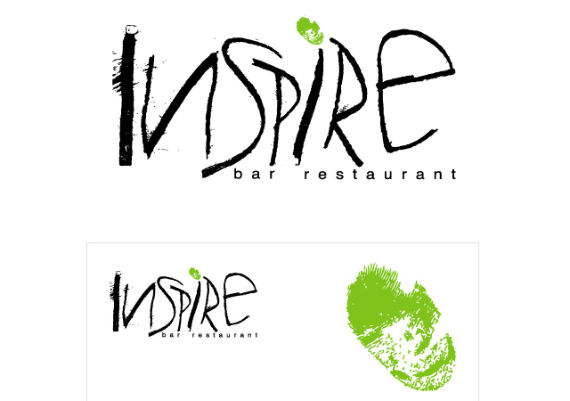
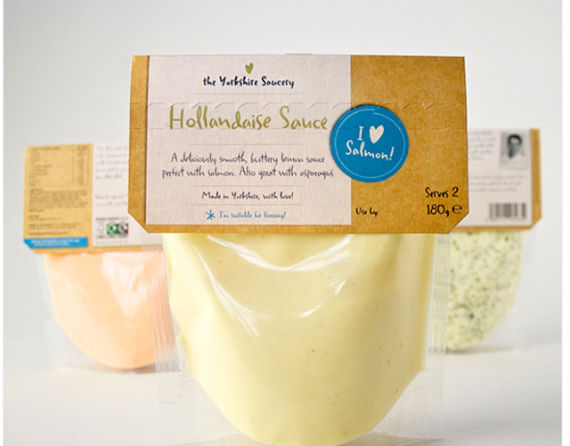
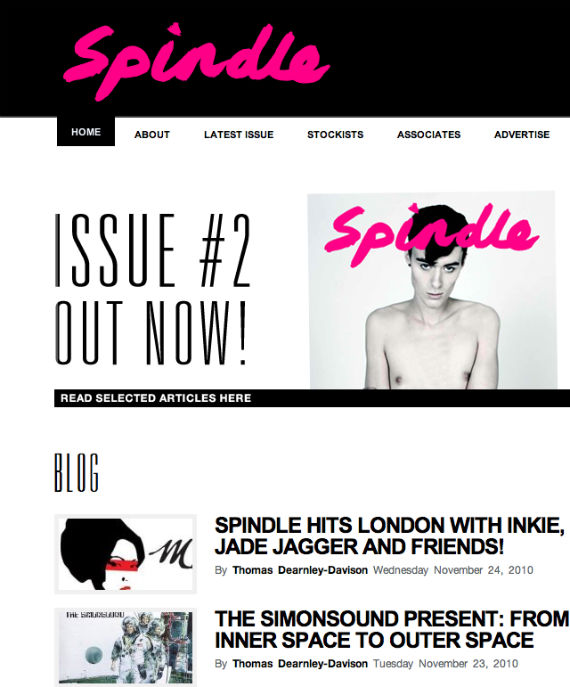
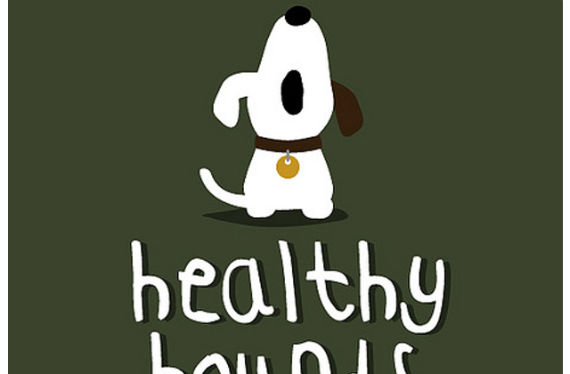
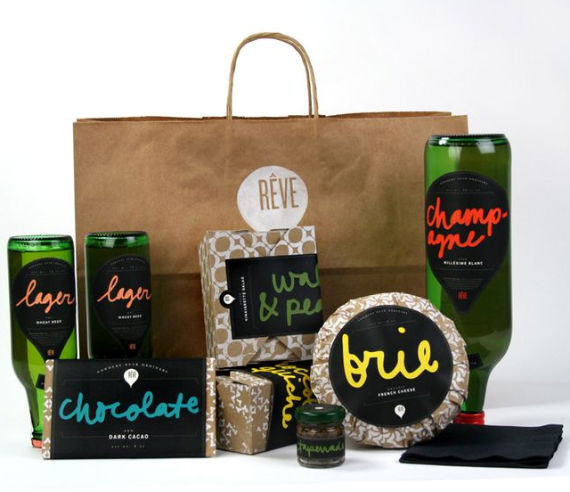
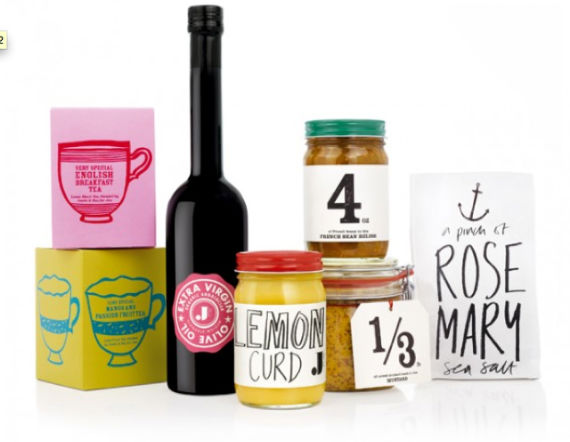
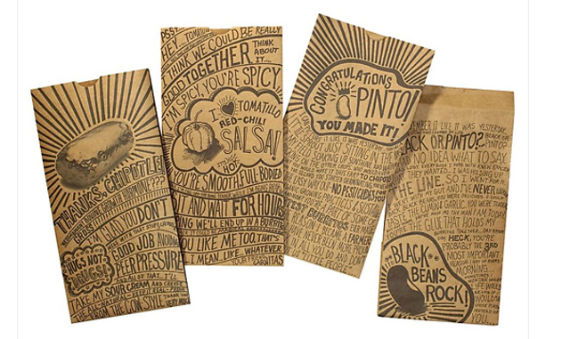
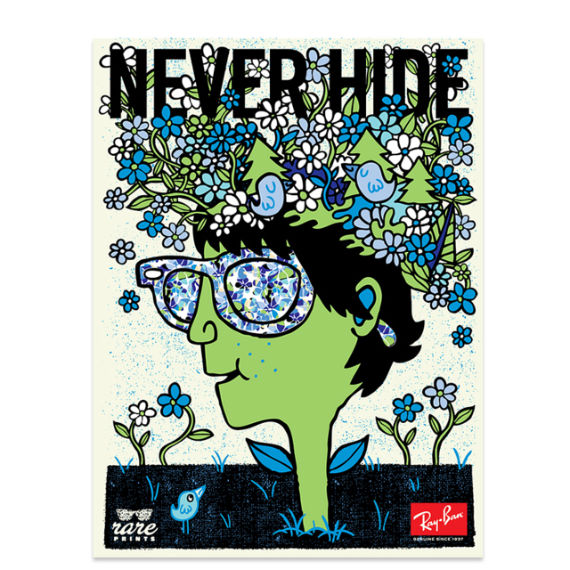
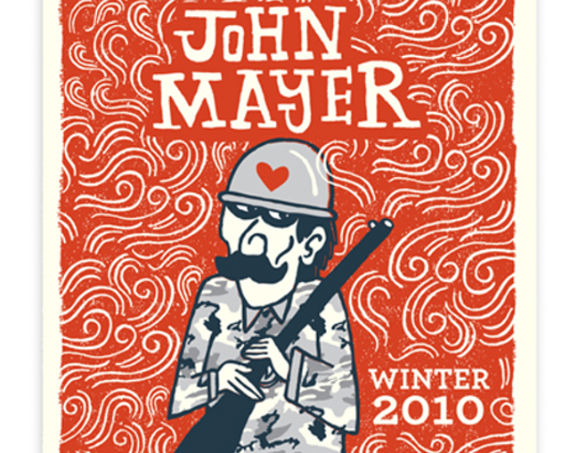
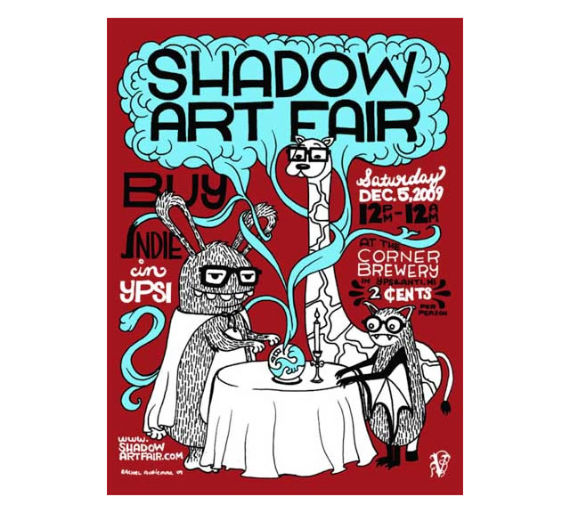
Je trouve que la typographie dessinée à la main donne un ton plus personnalisé aux pièces. J’aime beaucoup les emballages «Les produits Laura Berglund» qui sont épurés avec l’écriture dessinée en gros; elle devient un élément graphique important qui appuie le branding. Tout autant que Les produits Jamie Oliver avec le pot de moutarde entre autres!
J’aime aussi Linzie Hunter qui a utilisé l’écriture pour en faire une illustration complexe.
Tout comme toi Josée, j’ai vraiment aimé l’illustration Linzie Hunter. J’adore voir des pièces graphiques mélanger et utiliser plusieurs typographies. Pour les produits Laura Berglund et Jamie Oliver, l’emploi d’une telle typographie me donne l’impression que les produits sont organiques ou biologiques. 🙂